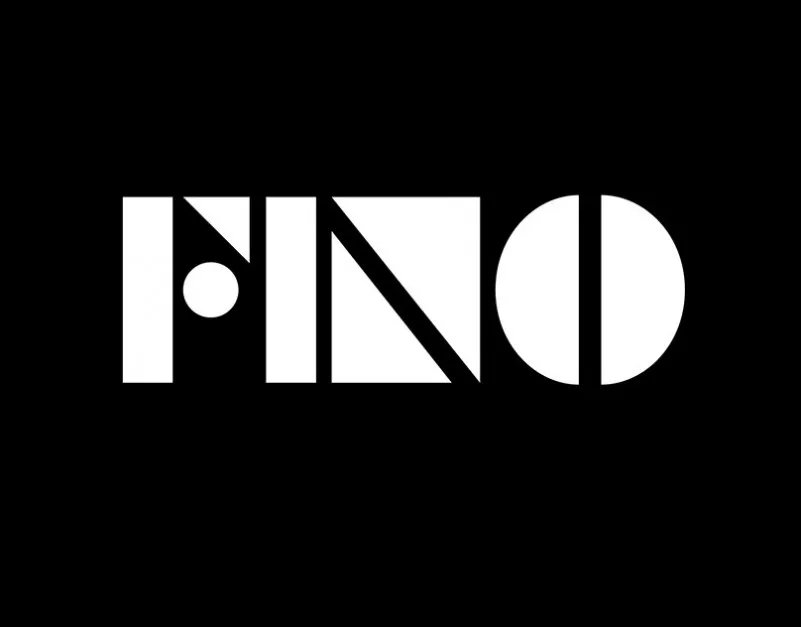
A Fino Black Font é uma opção incrível para designers amadores e profissionais que buscam um estilo moderno e divertido para seus projetos. Inspirada no trabalho de dois criativos talentosos, Sasha Iacob e Vlad Poparlan, esta fonte traz elementos geométricos com uma leve pitada de desenho artístico. Seu design é bold e encantador, construído através da combinação de triângulos, retângulos e círculos. Com seu traço firme e agradável aos olhos, a Fino Black Font se destaca como uma opção elegante para nomes de marca ou qualquer elemento gráfico que deseje destacar. Esta fonte é perfeita para aqueles que desejam adicionar um toque único e moderno às suas criações digitais, tornando-a uma escolha atraente em nossa categoria de Fonts Display. Não hesite em experimentá-la no seu próximo projeto gráfico; certamente não será apenas uma fonte, será um detalhe que marcará sua obra!